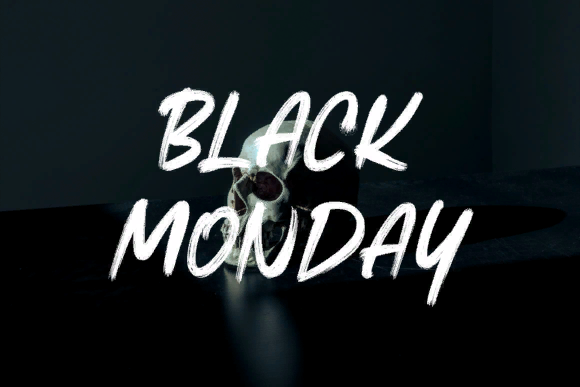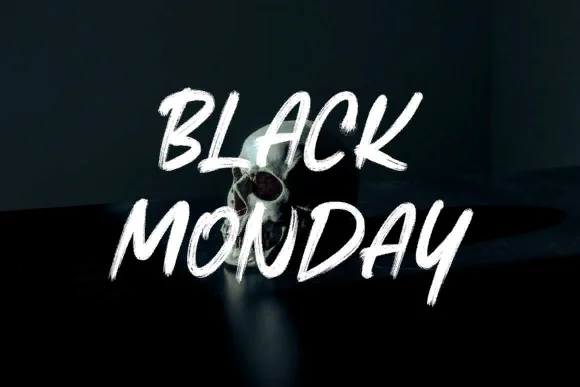
Название: Black Monday Font (2021)
Black Monday - это классный дисплейный шрифт с матовым начертанием.
Независимо от темы, этот шрифт станет отличным дополнением к вашей библиотеке шрифтов, поскольку он способен придать значимость любому творению.